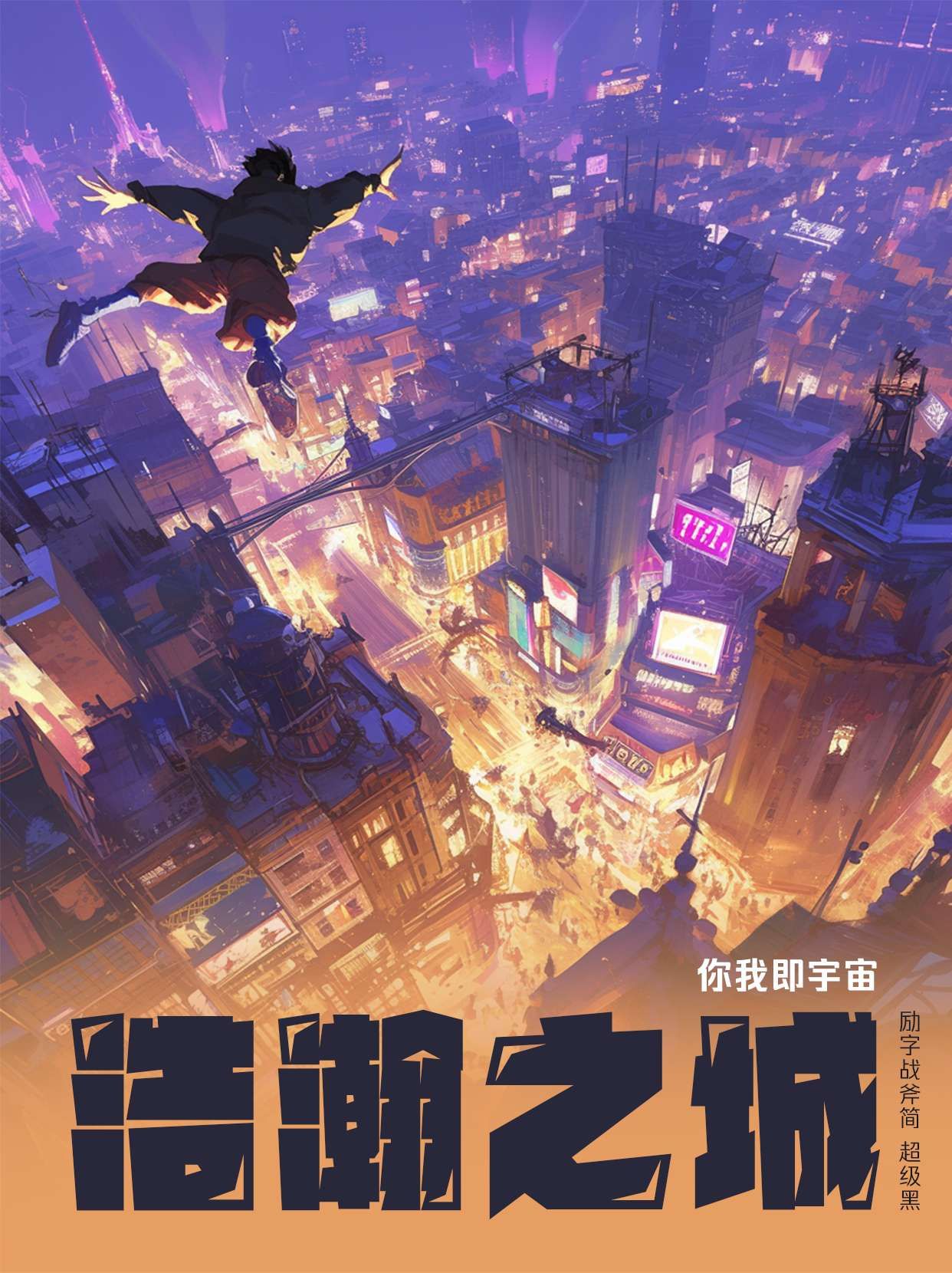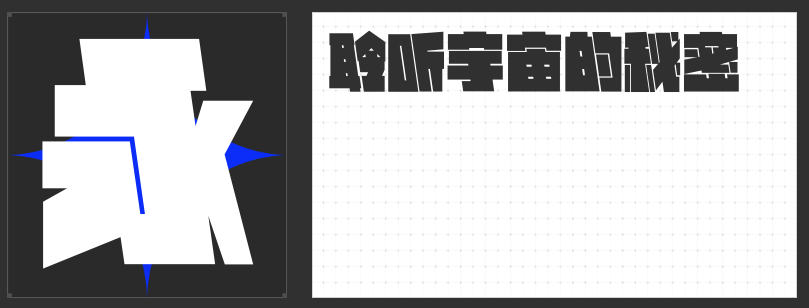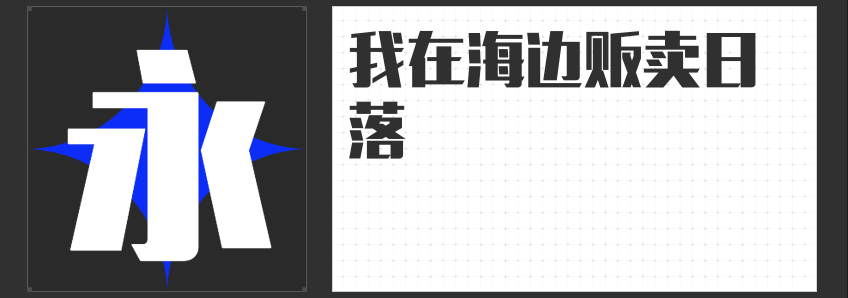
创意无限,字由心生 —— 四款励字造系列创意字体推荐
在视觉设计日益多元化的今天,一款独特的字体往往能为作品增添不少魅力。今天,就让我们一起探索四款来自励字造系列的创意字体,它们各具特色,无论是商业应用还是艺术创作,都能让你的作品脱颖而出。
首推“励字造飞行黑 超级粗”。这款字体字形方正,字面饱满,笔画粗重错落有致,整体视觉向左倾斜,带来一种强烈的动感。笔画棱角分明,重心平稳,空间结构紧凑,视觉效果震撼。它充满了力量与豪放,厚重的质感让人过目难忘,非常适合用于需要强调力量感和视觉冲击力的设计作品中。
接下来是“励字造战斧黑”。这款现代创意型黑体,字型厚重而不失开放性,笔画粗细不均,横竖笔画呈梯形分布,展现出独特的创意风格。撇、捺、点等笔画中融入了更多梯形元素,使得整体风格更加硬朗。左上和右下的对角高光设计,更是增强了风格的突出性,大标题字特征明显,现代文艺气息浓厚。
再来看看“励字造仲夏简 常规”。这款字体将清新文艺与传统相结合,笔画清晰坚挺,边缘略带斑驳,钩笔处理随意洒脱,透露出手写字的力量与果敢。字型端正,通用性强,无论是商业海报、包装设计,还是短视频、新媒体领域,都能轻松驾驭,展现出独特的韵味。
最后是“励字造灿烂黑”。这款中文字体笔触粗实,字形端正大气,视觉效果极佳。它适用于艺术设计、平面宣传设计、网页设计、海报设计等多个领域,能够很好地提升作品的品质感和专业性。
这四款励字造系列创意字体,每一款都蕴含着独特的风格和魅力,等待着你去发掘和应用。在设计的世界里,选择一款合适的字体,往往能让你的作品更加出色。